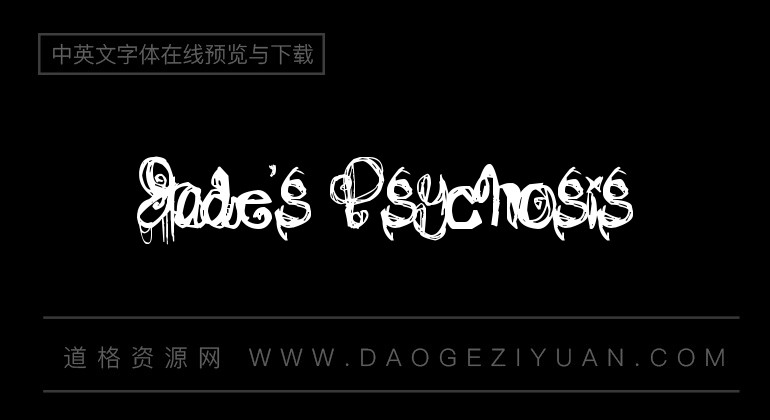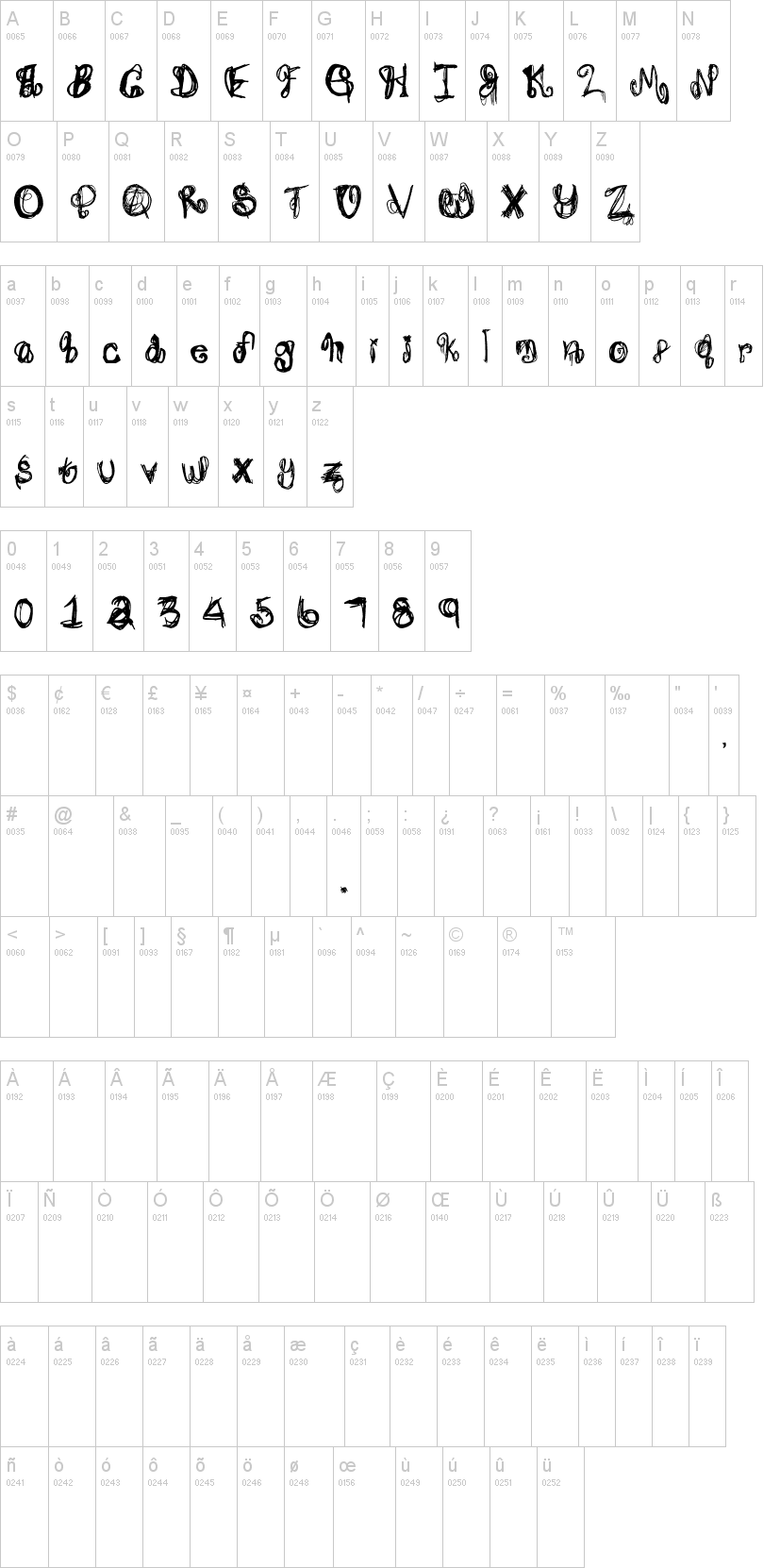
Jade's Psychosis 是一款独特的字体,由设计师Jade Hwang创作。字体灵感来源于她的精神病,具有独特的视觉效果,充满着神秘、梦幻、非凡的气息。它采用了一种复古风格的设计,拥有复杂的笔画,呈现出有趣的形状和节奏感。字体的设计灵感来源于Jade Hwang的精神病,具有独特的视觉效果,充满着神秘、梦幻、非凡的气息。它的特点是笔画简洁,但又有趣,可以用来创造出一种独特的视觉效果,从而让文字更具有表现力。内容介绍
Jade's Psychosis是一款非常不错的手写艺术字体,具有很好的视觉感,适合于文化类的宣传设计、商业类品牌的广告和产品包装设计以及个性化文字排版等较多场景。